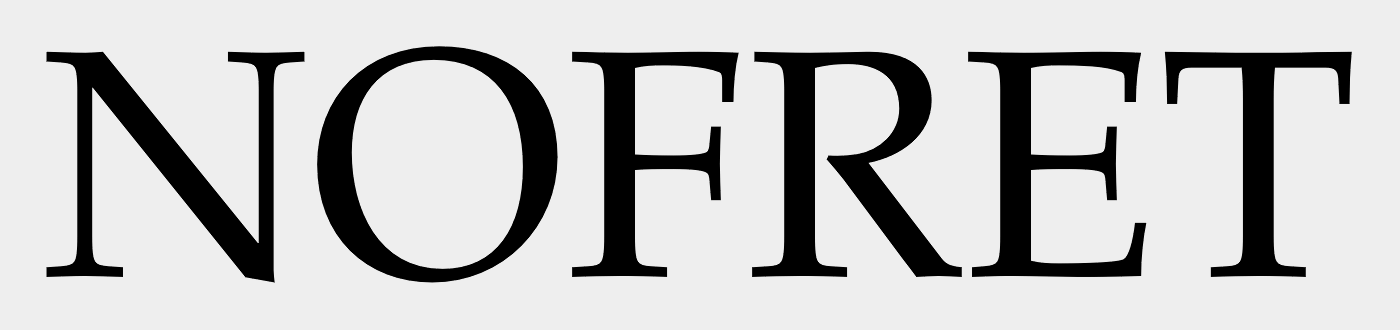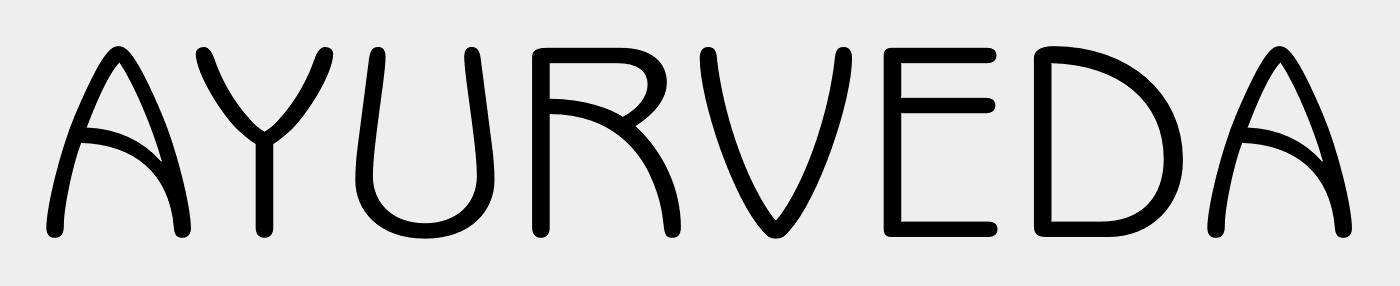
Schriftarten gesucht
ich benötige dringend die beiden Schriften auf dem Bild.
Ich weiß, die Qualität des Bildes ist miserabel, ich hoffe, irgendjemand kann mir trotzdem weiterhelfen.
Die erste Schrift ist der Times zumindest ähnlich...